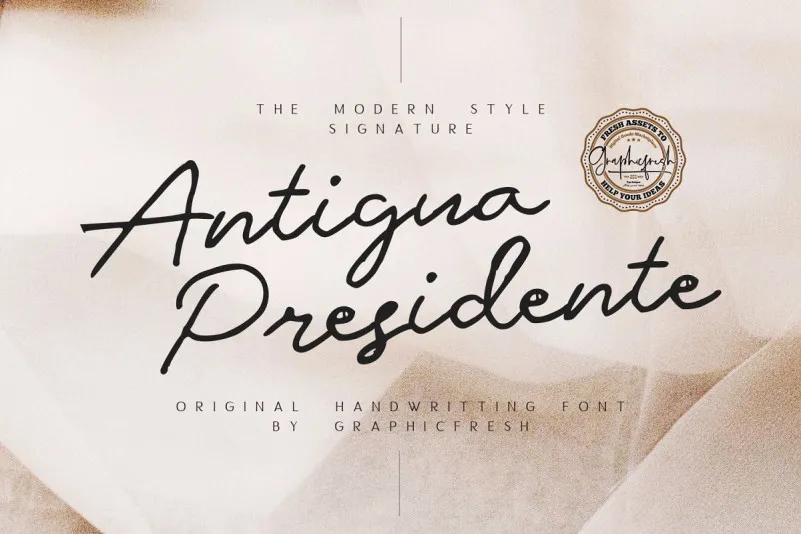
Antigua Presidente Script Font – Download Grátis
Antigua Presidente Font é uma magnífica adição à sua coleção de fonts. Desenhada pelo Designer 178-MC, esta script font oferece um toque distintivo e elegante para qualquer projeto gráfico. Seu design original e único a torna perfeita tanto para logos quanto para nome cards, layouts de magazines, cartas de convite ou até mesmo trabalhos grandes em tamanho. Se você está procurando uma fonte que possa destacar seu trabalho gráfico com um toque personalizado e profissional, Antigua Presidente será uma excelente escolha. Suavemente fluido e repleto de detalhes artísticos, esta font é perfeita para aqueles momentos em que queremos dar um toque especial a nossos projetos. Com certeza, ela vai fazer sua marca única ainda mais marcante.